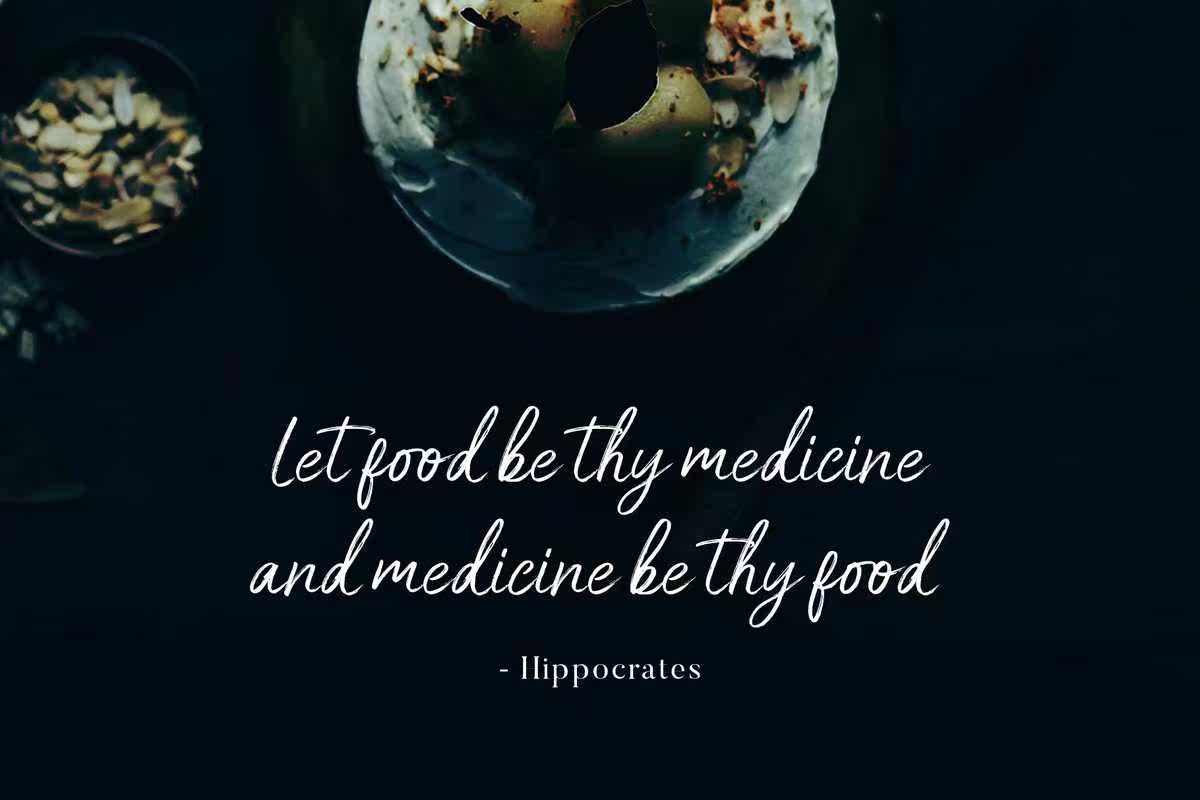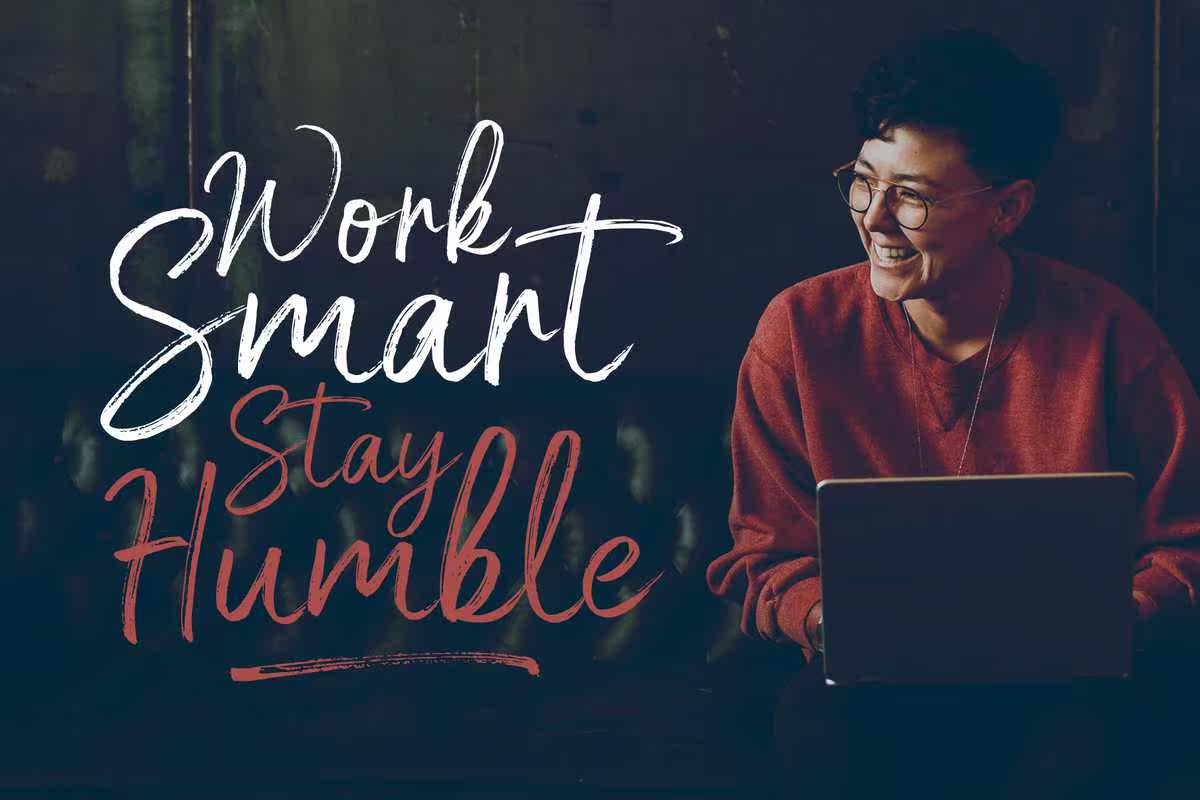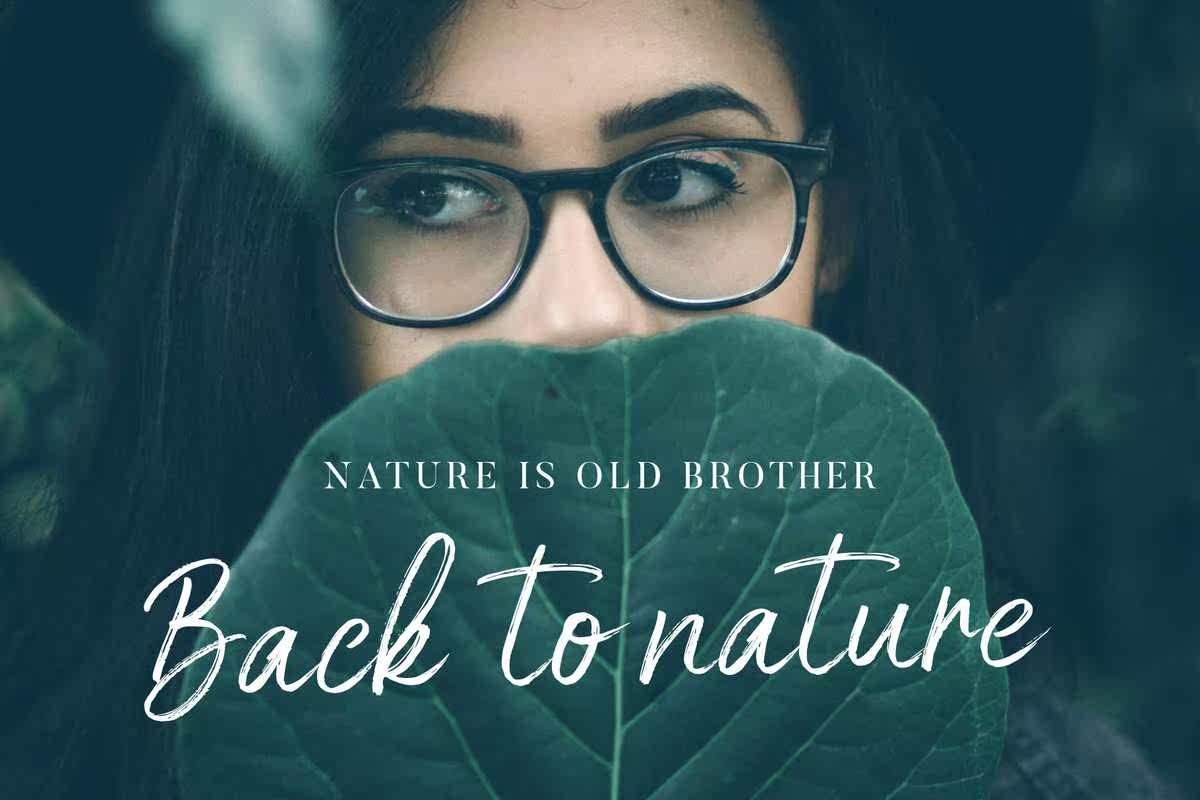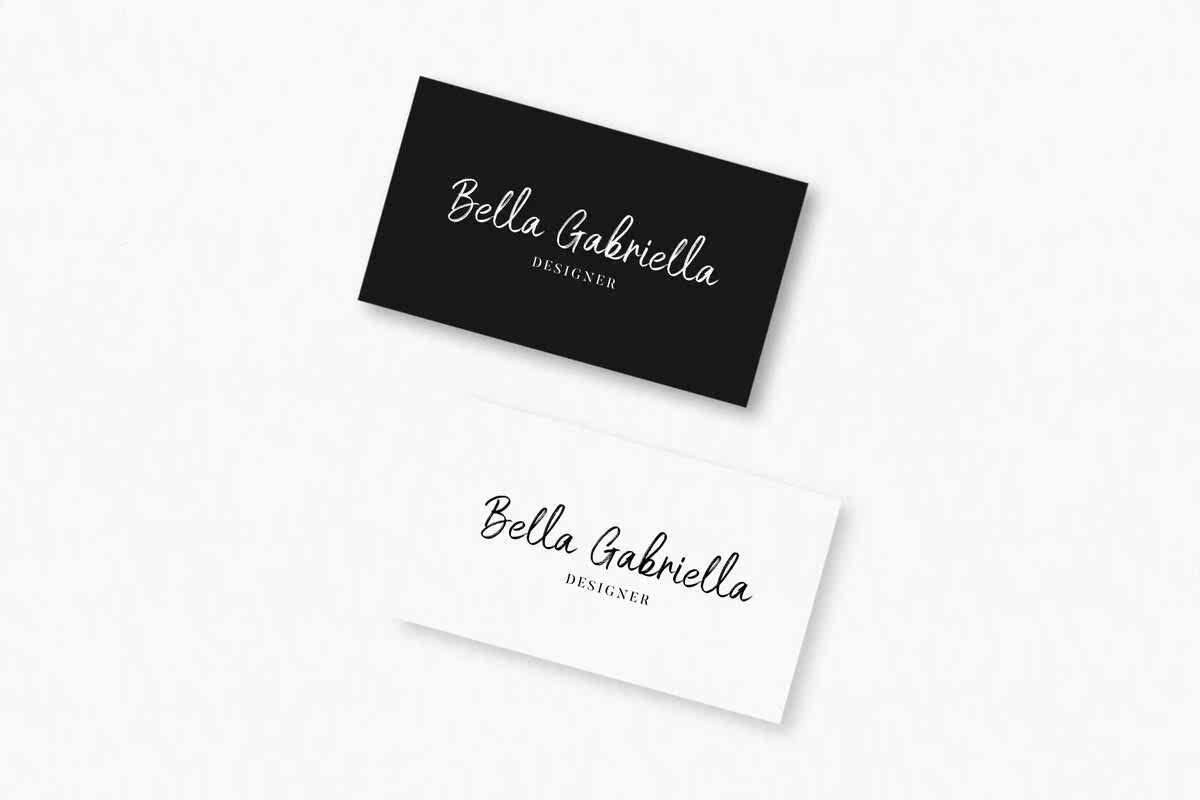
WhiteButterlish和WritenBrushScriptFont。它是一种自然风格的RyMarker,适用于品牌、广告、posterdesign、徽标、封面、杂志、包装、网站标题、问候卡、装置标志、商品、时尚活动、时事通讯、专辑封面、,和QuotedDesigns和More.Whitebuttellish和WritenBrushScriptFont。这是一种自然风格的RyMarker,它在品牌、广告、posterdesign、徽标、书皮、杂志、包装、网站标题、问候卡、服装标志、商品、时尚活动、时事通讯、专辑封面和QuotedDesigns和More方面非常完美。